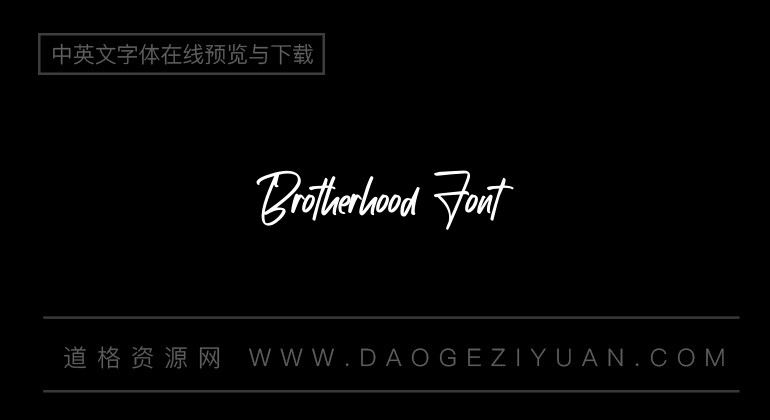
Brotherhood Font
Brotherhood Font 是一款免费的手写风格字体,由美国设计师 Andrew Littmann 设计。它的风格非常适合于品牌标志、海报、印刷设计、包装设计、T恤设计和手写风格的网站设计等。它是一种带有浓重笔画的手写风格字体,适合用于各种类型的设计项目。Brotherhood Font 包括大小写字母、数字、标点符号和一些特殊字符,可以与 Adobe Illustrator、Photoshop、InDesign 和 Microsoft Word 等软件一起使用。
Brotherhood Font是一款非常不错的手写艺术字体,具有很好的视觉感,适合于文化类的宣传设计、商业类品牌的广告和产品包装设计以及个性化文字排版等较多场景。